Handwritten Font Bundle
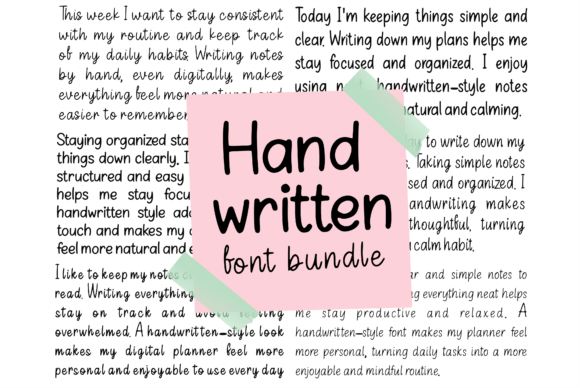
Handwritten Font Bundle gibi yüksek kaliteli varlıklar arıyorsanız, bu premium paket yaratıcı projeleriniz için harika bir seçimdir.
Hassasiyetle hazırlanan Handwritten Font Bundle, temiz vektörler, pürüzsüz tipografi ve içinizin rahat etmesi için ticari bir lisans sağlar.
İster İsteğe Bağlı Baskı (POD) ürünleri, ister düğün davetiyeleri veya sosyal medya grafikleri oluşturuyor olun, Handwritten Font Bundle ideal bir uyumdur.
Uzman ipucu: Pazarda öne çıkan benzersiz, göz alıcı tasarımlar oluşturmak için bu öğeleri tamamlayıcı yazı tipleriyle birleştirin.